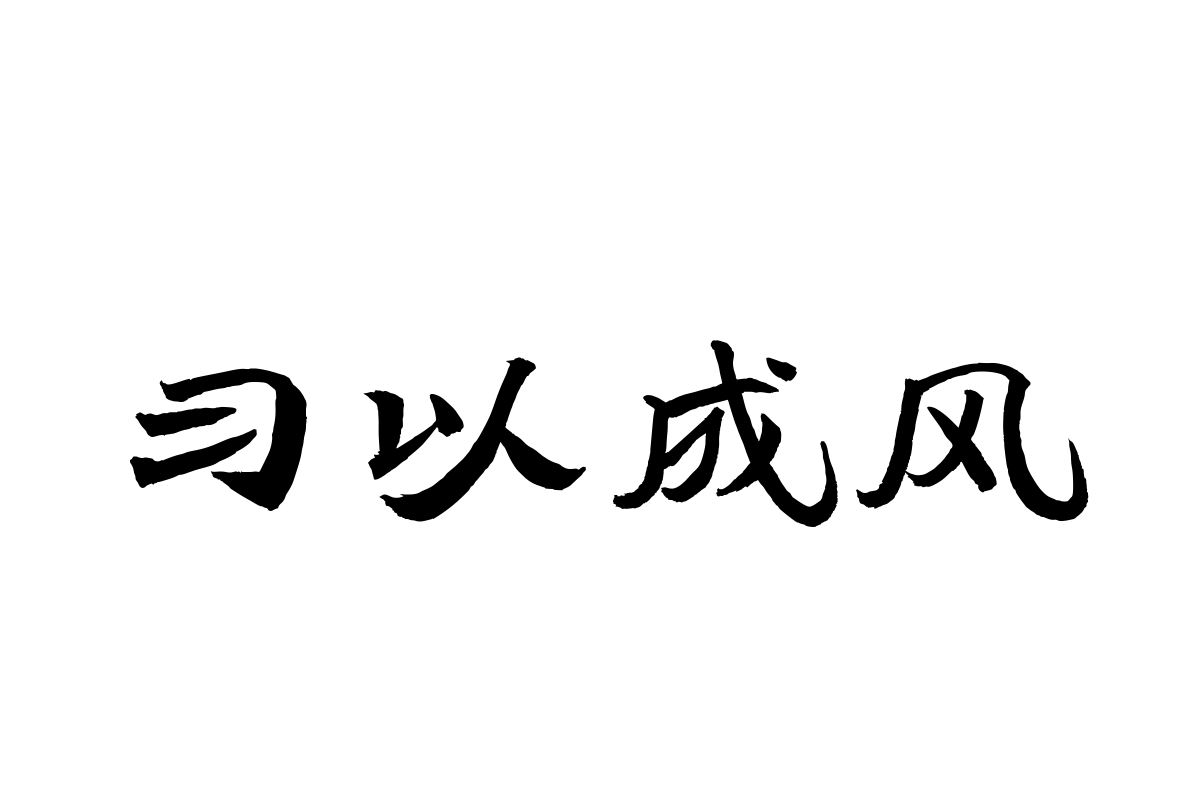
汉仪范笑歌古魏是一套由汉仪字库公司开发的字体,具有独特的书法风格和强烈的视觉冲击力。这套字体采用了传统的魏碑风格,笔画粗犷有力,线条流畅自然,给人一种古朴而庄重的感觉。同时,它还融入了一些现代的元素,使得整体风格更加现代和时尚。
汉仪范笑歌古魏字体适用于各种需要展现传统文化和艺术气息的场合,如广告设计、包装设计、书籍装帧等。它的使用能够有效地提升设计的档次和品味,使作品更具特色和吸引力。